タイププロジェクトでは、赤入れと修正を何度も繰り返してフォントの品質を高めていきます。今回からのシリーズでは、TPスカイファミリー制作時の資料からの赤入れをいくつか取り上げて、その指示内容を紹介していきます。
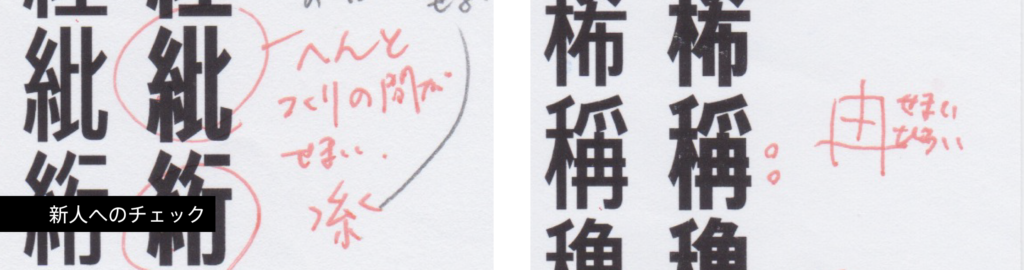
これは私が入社1年目の時、制作した漢字に先輩が赤入れをしてくれたものです。「紕」は偏と旁の間が狭いから糸偏の幅を狭くしてあいだを少し開けるように、「稱」は「冉」のカウンターを上が狭く・下が広くなるようにする、といった内容が書き込まれています。新人向けに基本的な作り方の指導も含めた赤入れなので丁寧に指示がありますが、慣れてくると簡略化した赤入れが増えてきます。
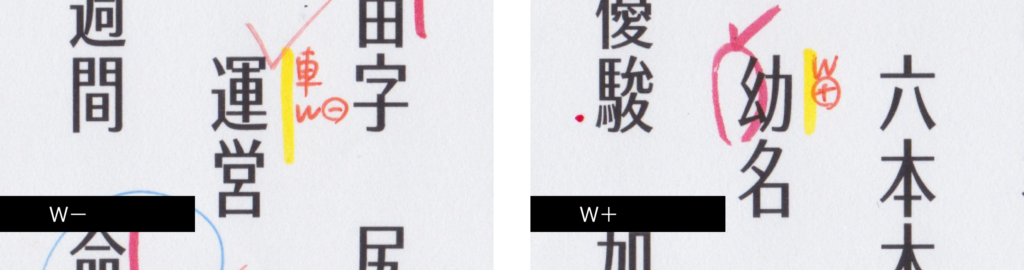
例えば、W-とW+はよく登場します。Wはウエイトの意味で、W-なら「筆画を細く」、W+なら「筆画を太く」です。この場合は、「運」の「車」だけ細く、「幼」の「⺓」だけ太く、という指示になります。
数百字、数千字を一気にチェックすることもあるので、書き込みは簡潔にしてスピーディーに赤入れをしています。